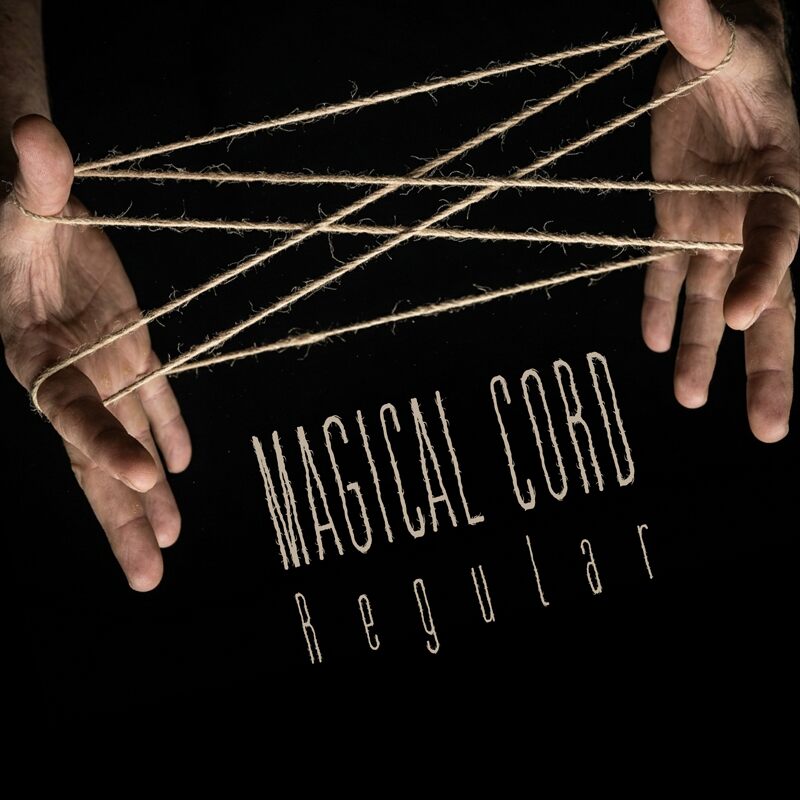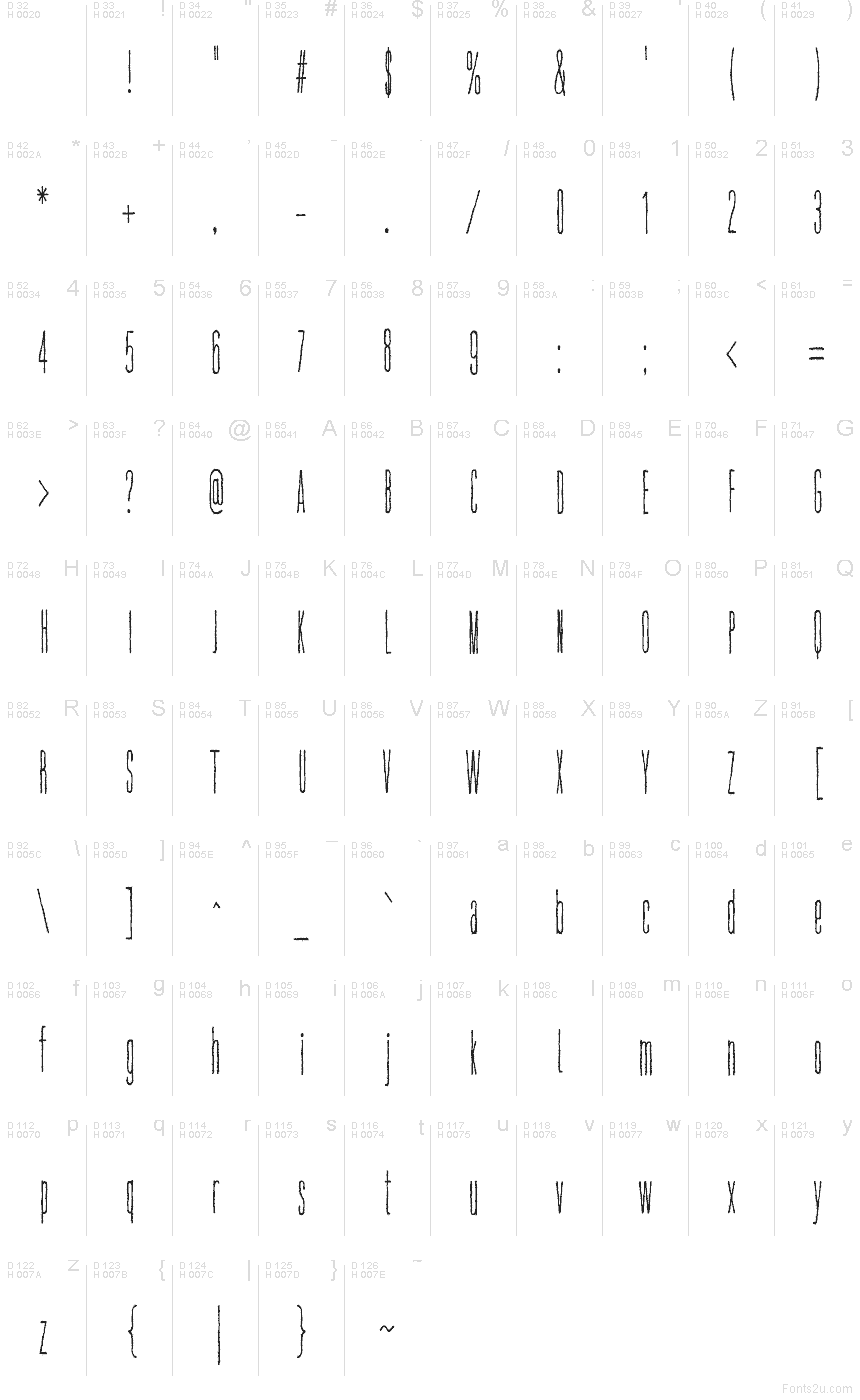
Magical Cord Regular
Magical Cord от Galdino Otten — это бесплатный рукописный шрифт в «проволочном» стиле с высоким, слегка хаотичным ритмом и мистическим, сказочным настроением. Буквы выглядят так, будто они скручены из тонкого шнура или нарисованы дрожащей линией пера: узкие формы, неуверенные штрихи и длинные нисходящие петли создают нервную, живую текстуру.
Шрифт отлично подойдет для постеров, обложек независимых книг, названий зинов, заставок к фильмам и атмосферной упаковки, где требуется бесплатный шрифт, передающий ощущение ручной работы и необычный характер, но без излишней «миловидности». Используйте его для коротких заголовков, имен художников или буквиц, особенно если хотите, чтобы акцент был сделан на вертикальной вытянутости и паутинообразных петлях.